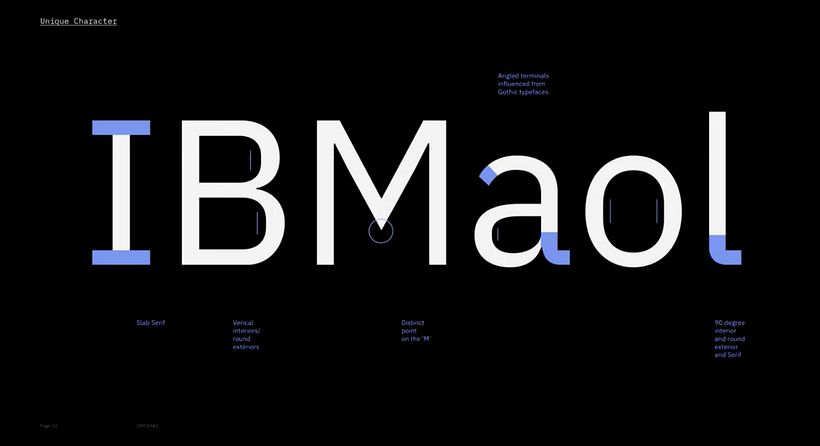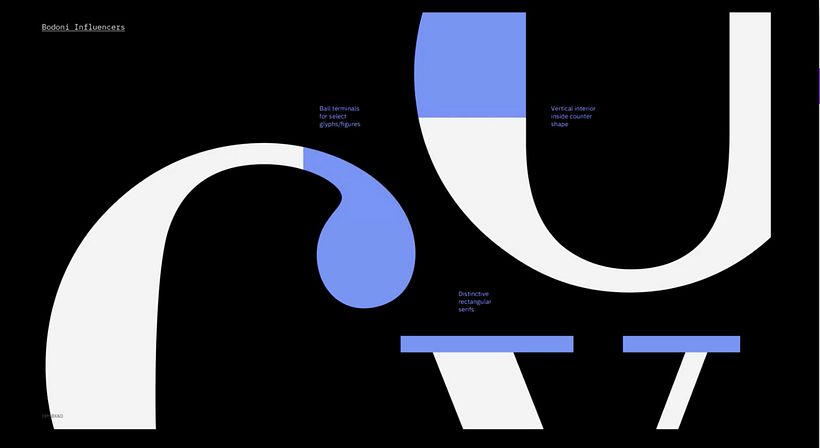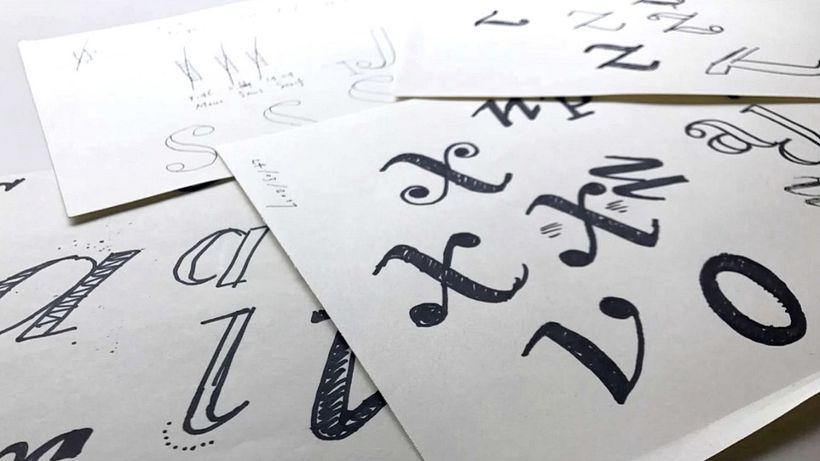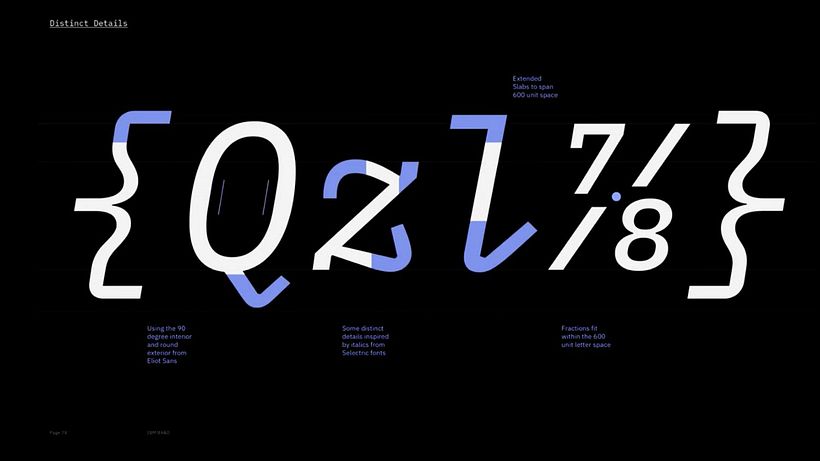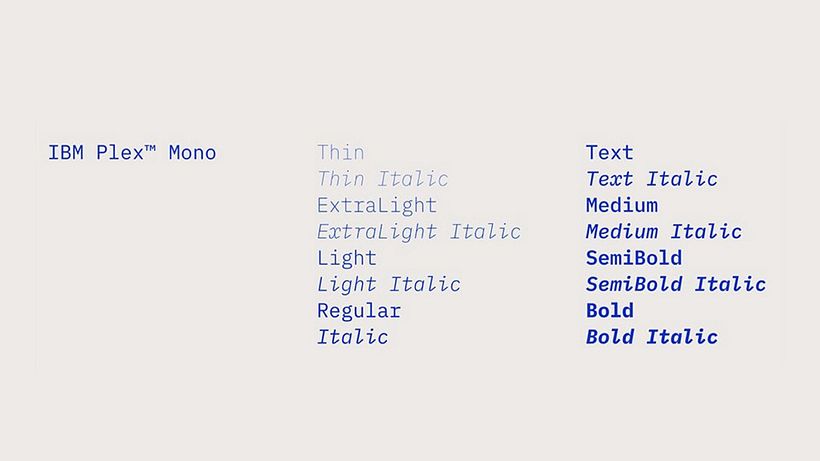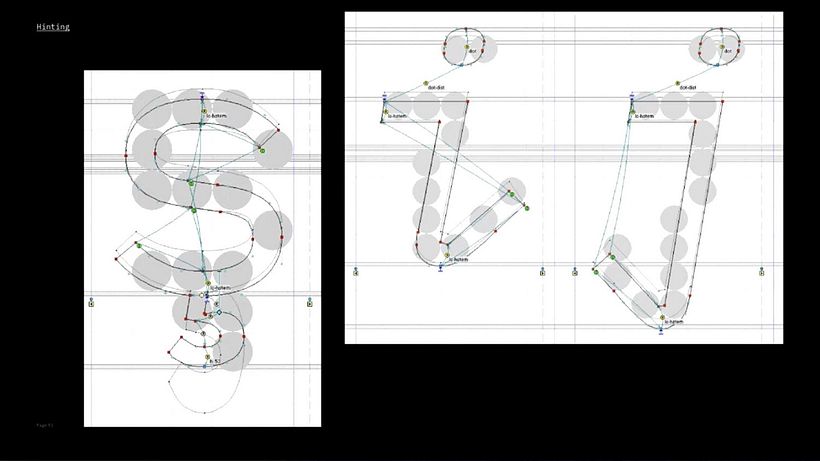
IBM diseña su tipografía corporativa open source
IBM deja de lado la Helvetica para diseñar y desarrollar su propia tipografía corporativa gratuita y open source.
A pesar de haberse posicionado como una compañía preocupada por el diseño desde sus inicios (su más que reconocible logotipo fue diseñado el mítico Paul Rand), IBM lleva años utilizando la tipografía Helvetica de manera corporativa; un tipo de letra que habla de modernidad, pero que ya queda lejos de reflejar el espíritu que IBM quiere mostrar a sus usuarios. Es por eso que ahora presentan IBM Plex, su nueva tipografía corporativa, que encierra en sus formas uno de los valores que han acompañado a la marca desde el principio de los tiempos: la relación del hombre con la máquina.
La nueva tipografía, que reemplazará el uso de la Helvetica en toda la comunicación visual de IBM, ha sido diseñada por el director creativo de la marca, Mike Abbink y su equipo de diseñadores. Esta decisión, no obstante, no responde exclusivamente a una necesidad de crear una fuente tipográfica que identifique los valores de la marca, sino que tiene su razón de ser también en su vertiente económica, ya que dejar de utilizar Helvetica ahorrará a IBM aproximadamente un millón de dólares al año.
IBM Plex es una familia tipográfica compuesta por tres ramas: una sans serif, una serif y una monospace, cada una de ellas con ocho pesos y estará disponible en 110 idiomas. De momento está disponible en formato open source, aunque durante el 2018 podrá descargarse también, gratuitamente, en Google Fonts.